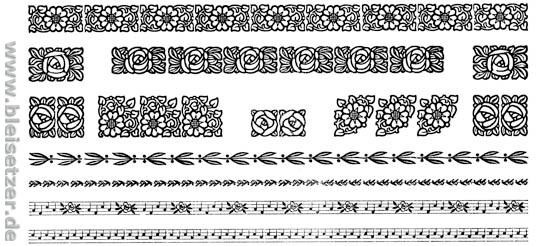
Schmuck-Vignetten
Im Bleisatz gibt es auch Schmuck-Vignetten. Zum Teil wurden diese auch von Typographen entworfen, wie z.B. "Tiemann-Schmuck", den er zusammen mit der Euphorion gestaltet hat - auf dem Bild zu sehen im mittleren Teil, die floralen Ranken:
So etwas gab es auch von Ehmcke, Herbert Post u.a.
Nun habe ich vor Jahren einmal von einer wissenschaftlichen Auswertung gehört bezüglich solchen Bleisatz-Schmuckes. Blöderweise sogar einmal ein Exemplar dieser Arbeit in einem Antiquariat gesehen, aber nicht sofort gekauft.